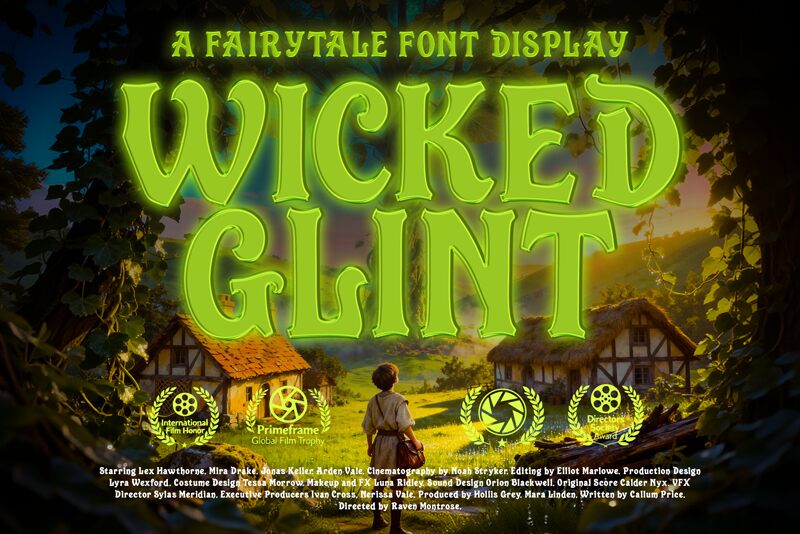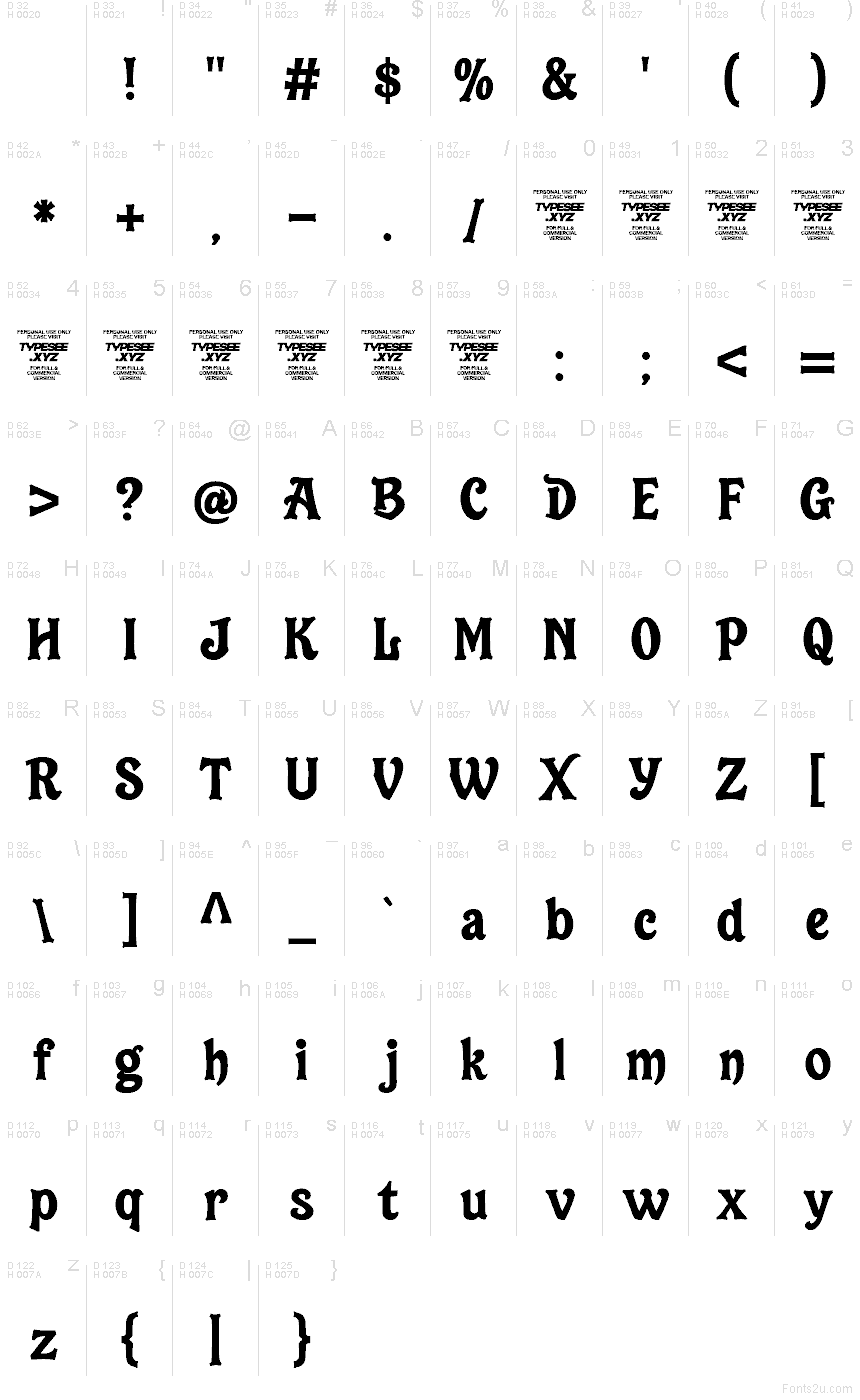
Wicked Glint, de Typesee Type Foundry, es una tipografía display retro gratuita con un aire alegre y de cuento de hadas. Las letras se sienten llenas y vivaces, con formas redondeadas, uniones estrechas y pequeños remates en forma de gota que le dan a las palabras un toque de picardía, alejándose de la rigidez vintage tradicional.
Encaja a la perfección en titulares de pósteres, packaging de boutiques, portadas de álbumes, menús de bar y títulos donde busques un acento retro juguetón sin llegar a ser demasiado caricaturesca. Al ser gratuita, también es muy útil para líneas de branding cortas, gráficos de eventos y logotipos, ya que sus curvas dinámicas y sus detalles afilados aportan muchísimo carácter incluso en palabras cortas.